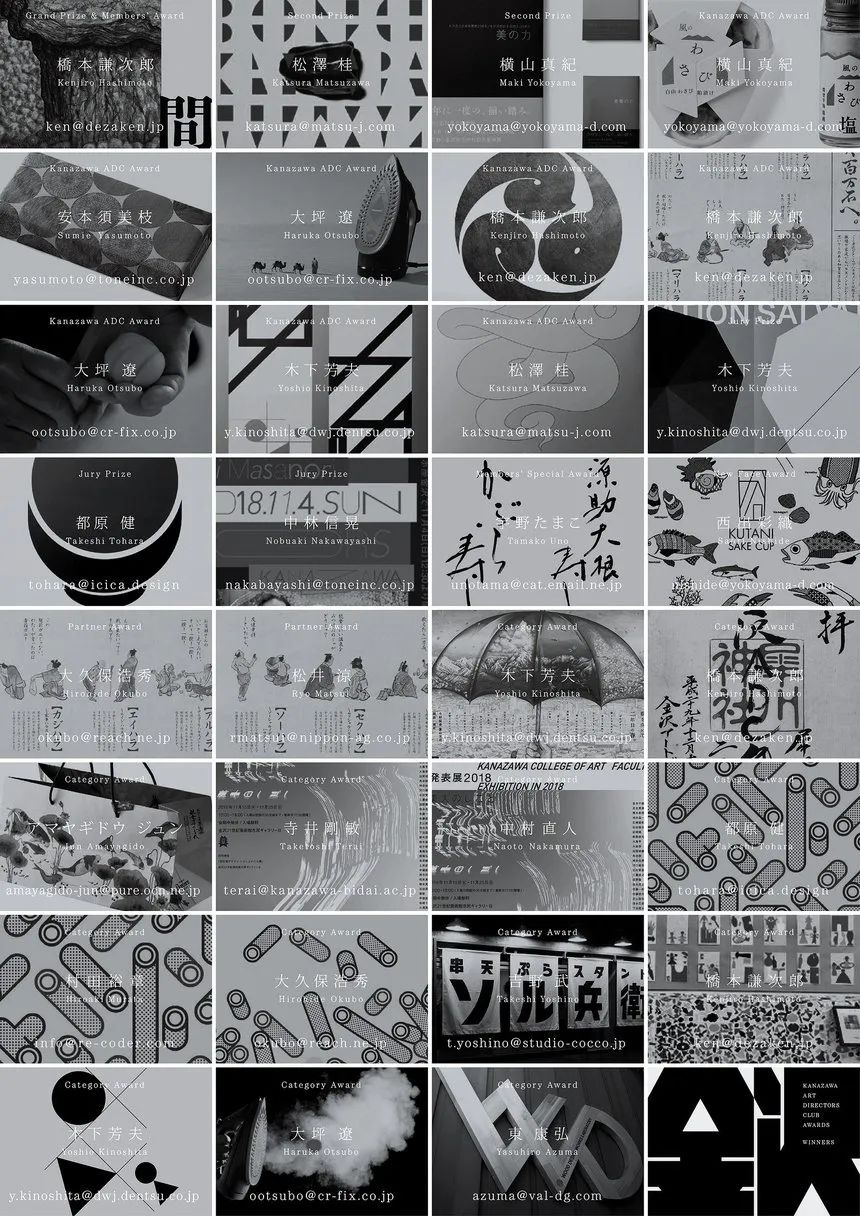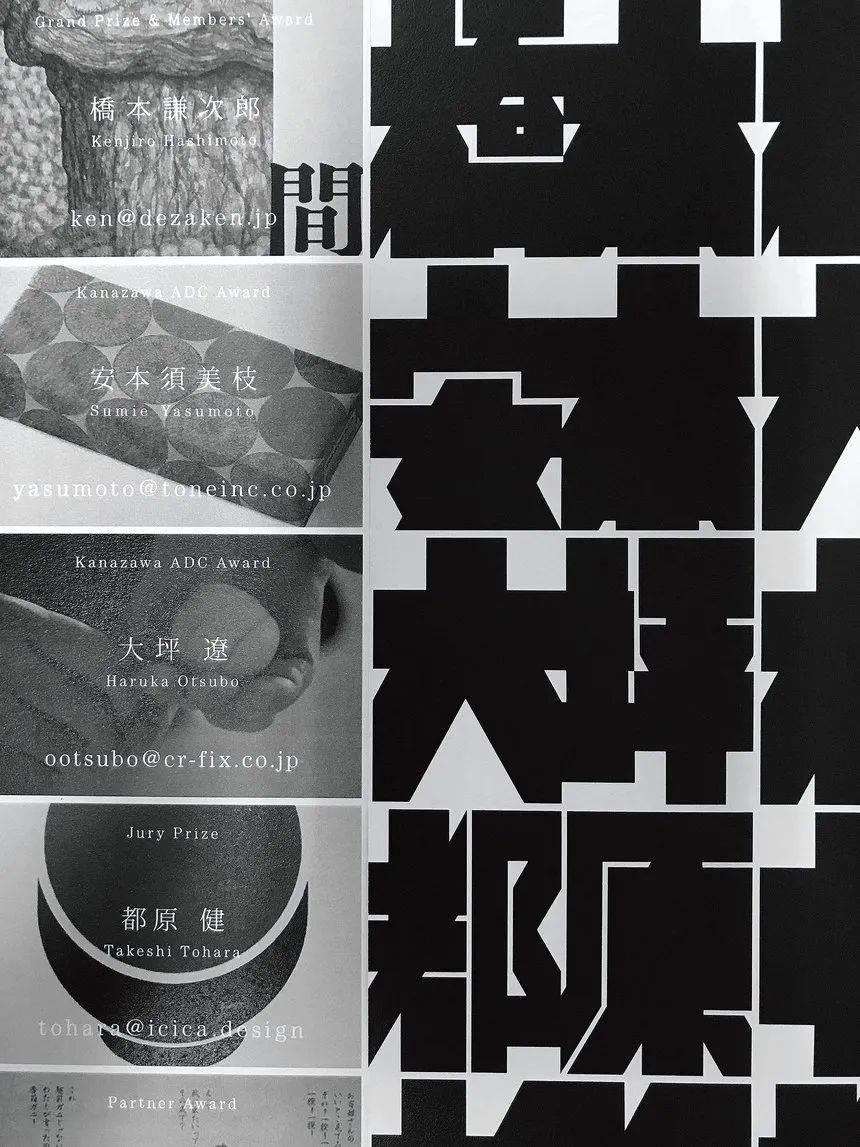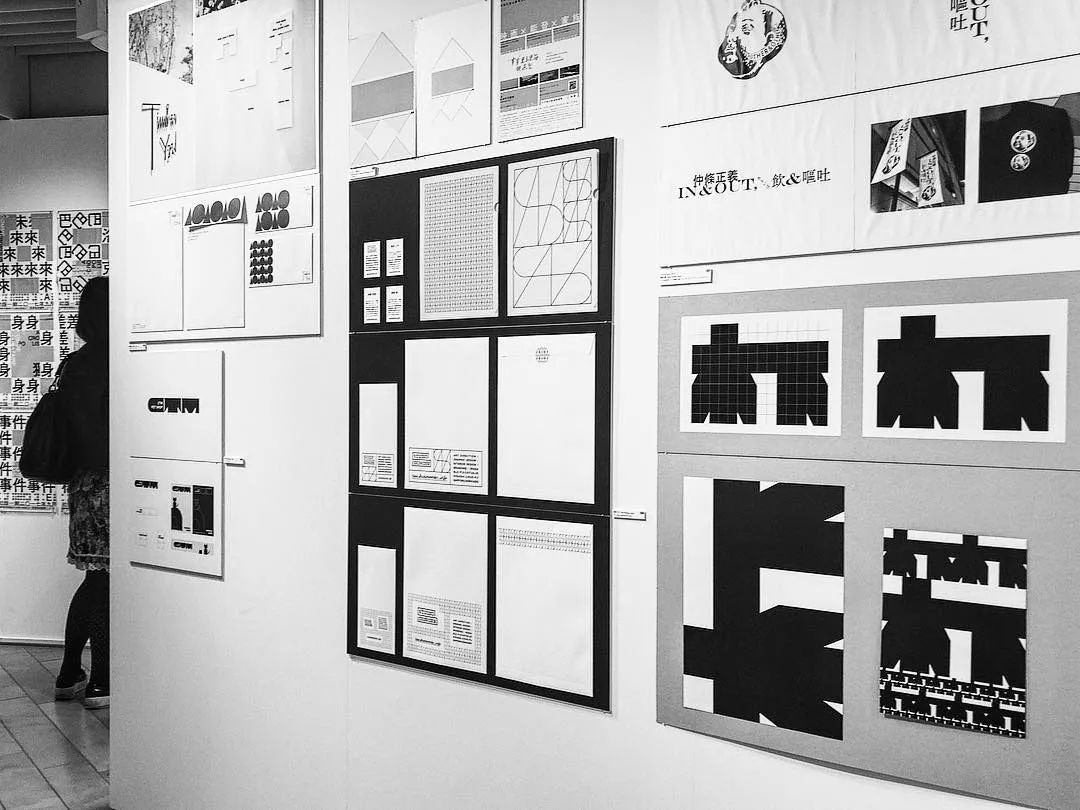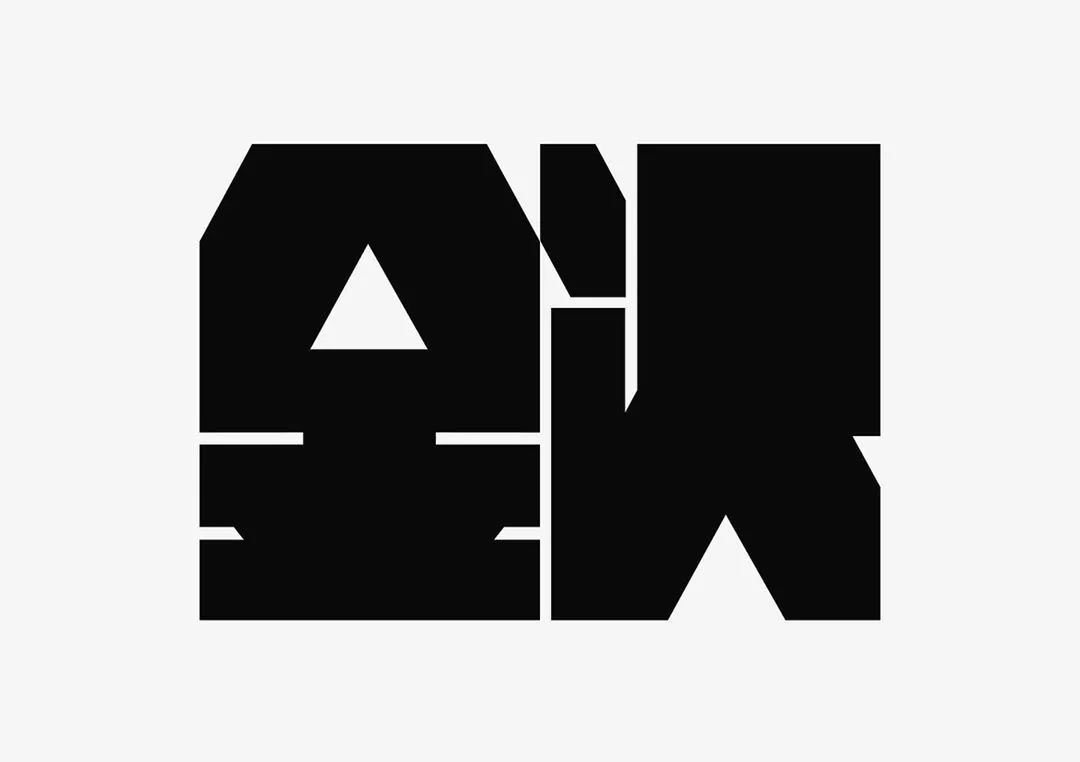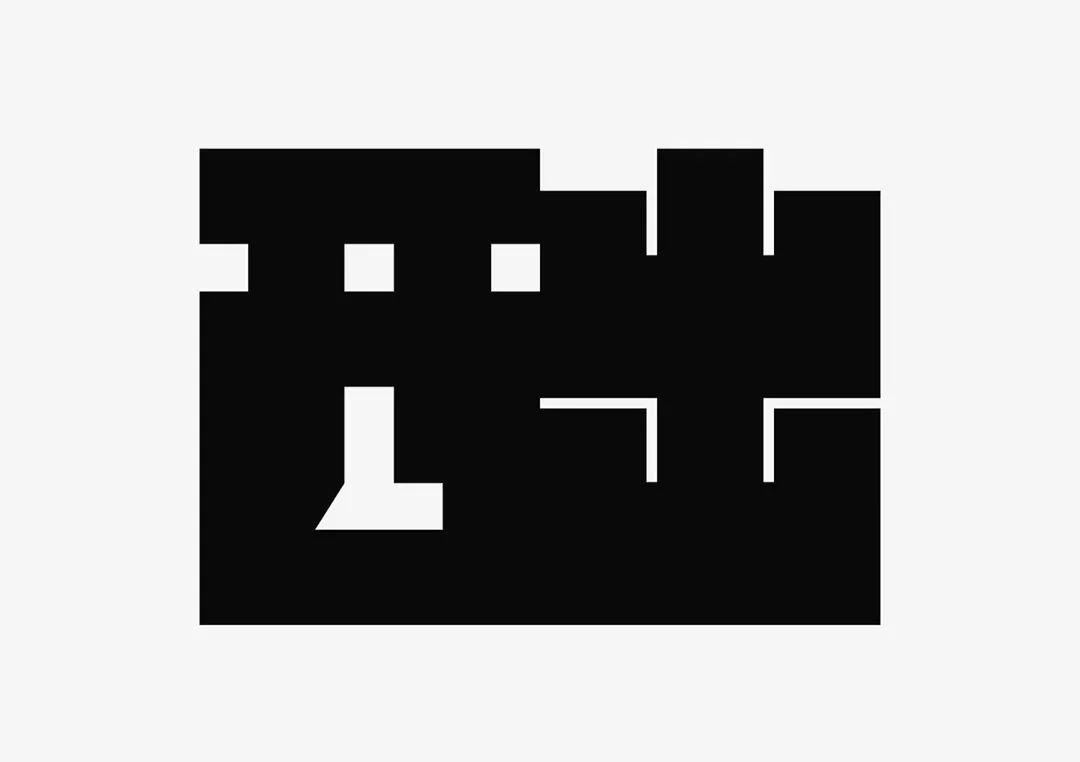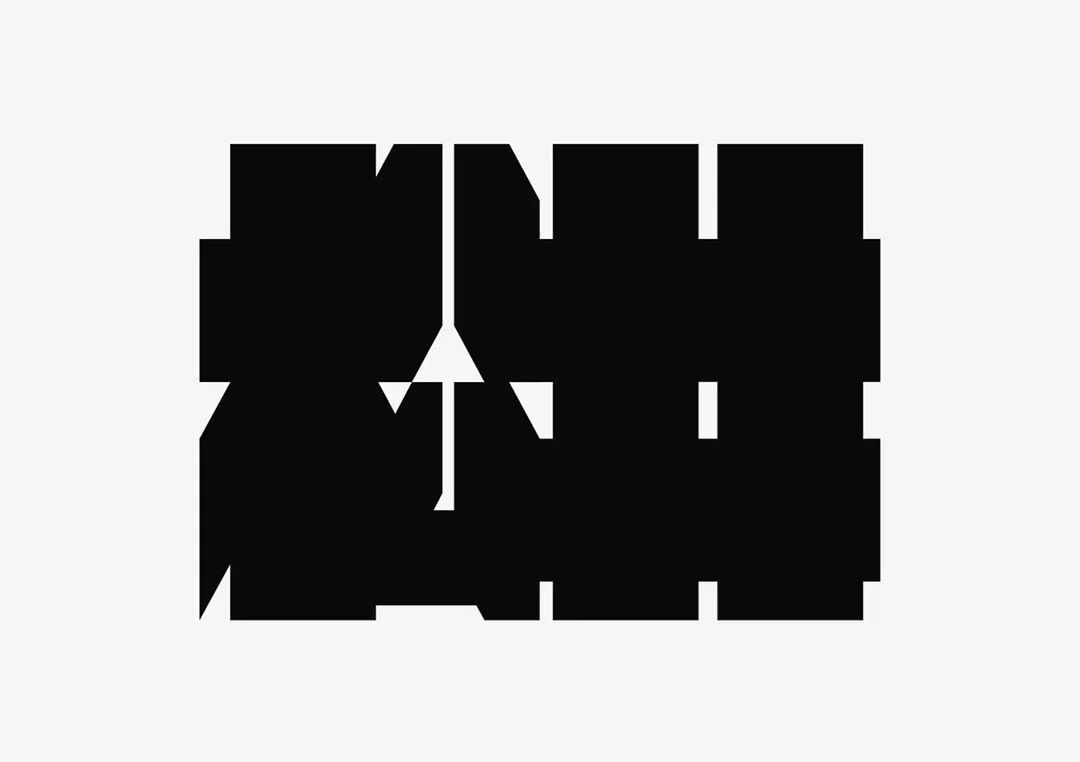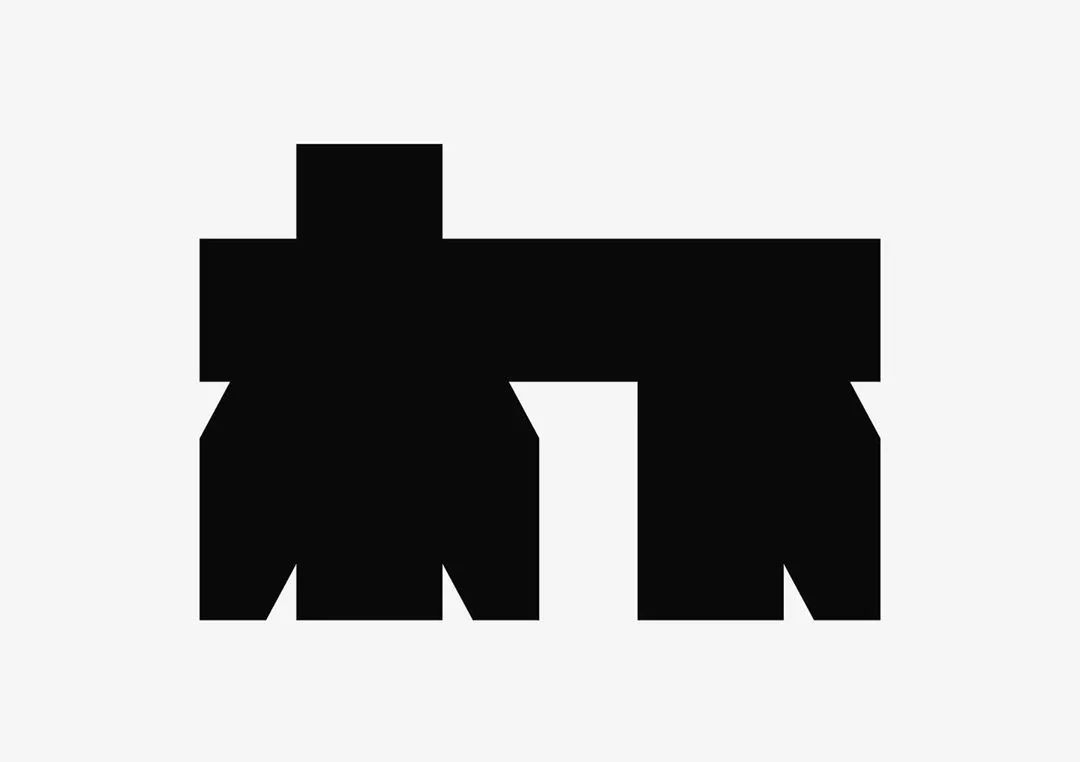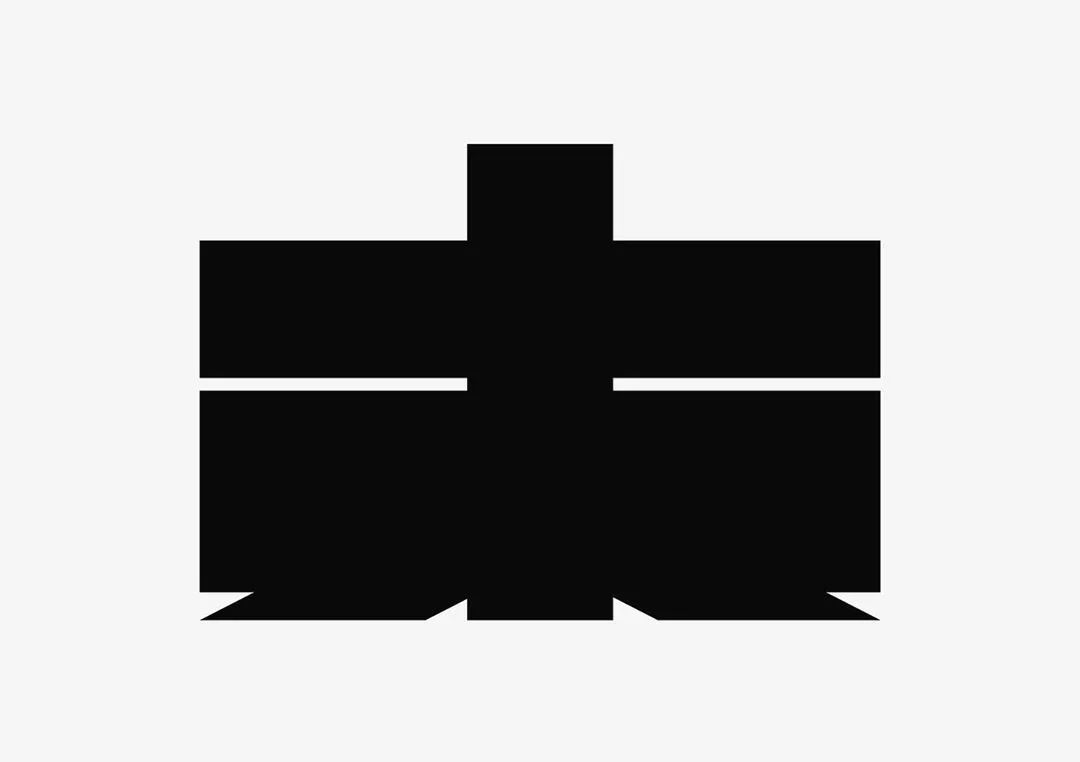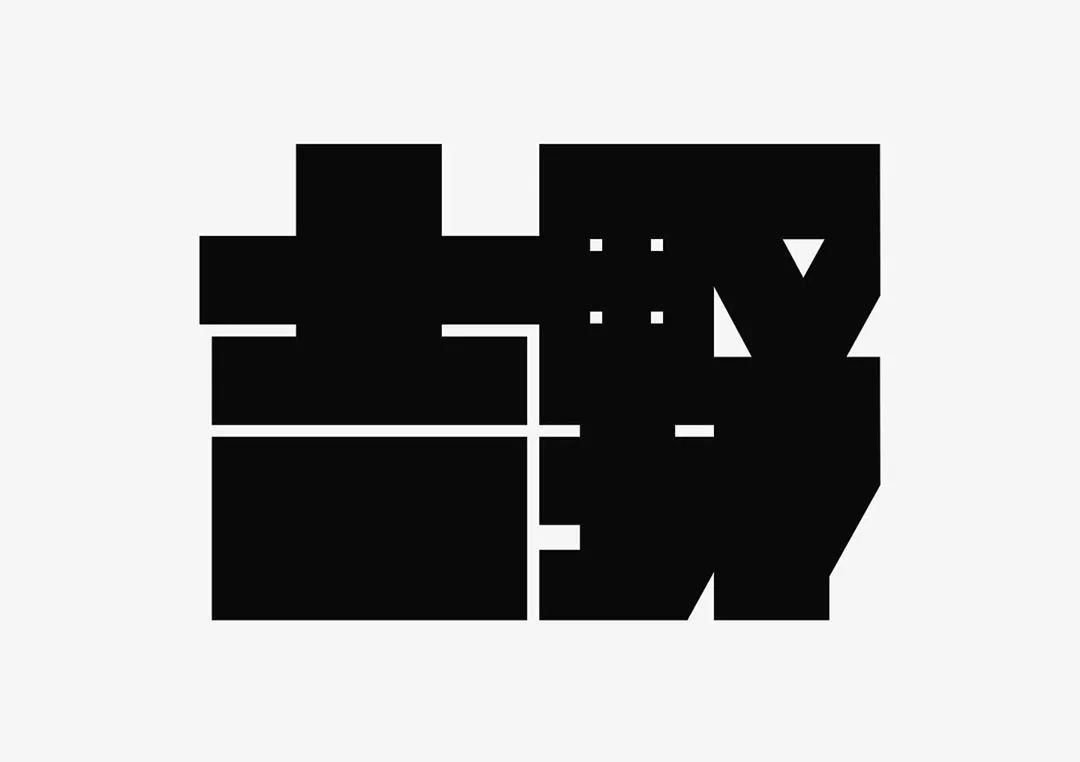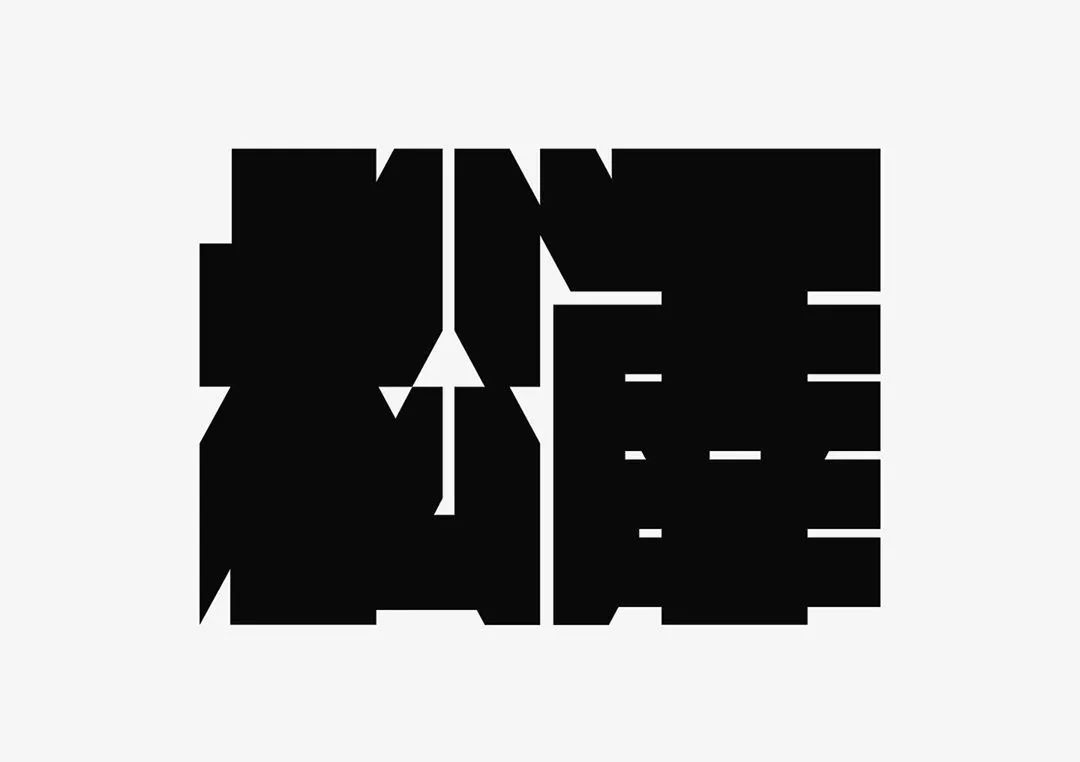
Yoshio Kinoshita の 汉字实验探索
由金泽ADC获奖者名字组成的海报
海报和物料的设计是由获奖的艺术总监的名字组成的。然后在获奖者展览上展出。金泽ADC奖:由日本金泽艺术指导俱乐部举办的奖项。
本次展览在石川县金泽县21世纪当代艺术博物馆和Nonoichi Kaleid举行。以汉字与获奖名字组成这次展览的海报,能迅速告诉你谁是获奖者。
400年前的日本。那个时代被称为江户时代。那时,江户书体诞生了。在日本,最粗的字被认为是一种好运。
在以前歌舞伎(剧院)、相扑(摔跤场)和娱乐场制作了带有表演者或参赛者姓名的招牌和海报。工艺美术大师名单也用粗体书法制作。这一设计可谓是金泽工匠大师名单的现代诠释。
该作品还获得D&AD2020版式类别的木铅笔奖,及纽约TDC传播设计类印刷卓越奖。
金沢
西出
松井
木下
東
吉野
松澤
服部
中林
横山
宇野
村田
橋本
大久保
中村
大坪
安本
寺井
都原
アマヤギ堂
日本汉字 = 获奖者姓名
橋本 / 松澤 / 横山 / 横山 /安本 / 大坪 / 橋本 / 橋本 /大坪 / 木下 / 松澤 / 木下 /都原 / 中林 / 宇野 / 西出 /大久保 / 松井 / 木下 / 橋本 /アマヤギ堂 / 寺井 / 中村 / 都原 /村田 / 大久保 / 吉野 / 橋本 /木下 / 大坪 / 東 / 金沢